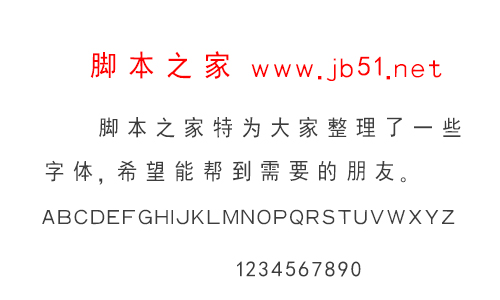
蘭米秀黑字體是蘭米字庫推出的一款中文藝術(shù)字體,字體筆觸粗細(xì)適中,具有很好的視覺感,適合應(yīng)用于藝術(shù)設(shè)計(jì)、平面宣傳設(shè)計(jì)、網(wǎng)頁設(shè)計(jì),書法字帖等領(lǐng)域,歡迎喜歡蘭米秀黑字體的朋友前來下載使用。